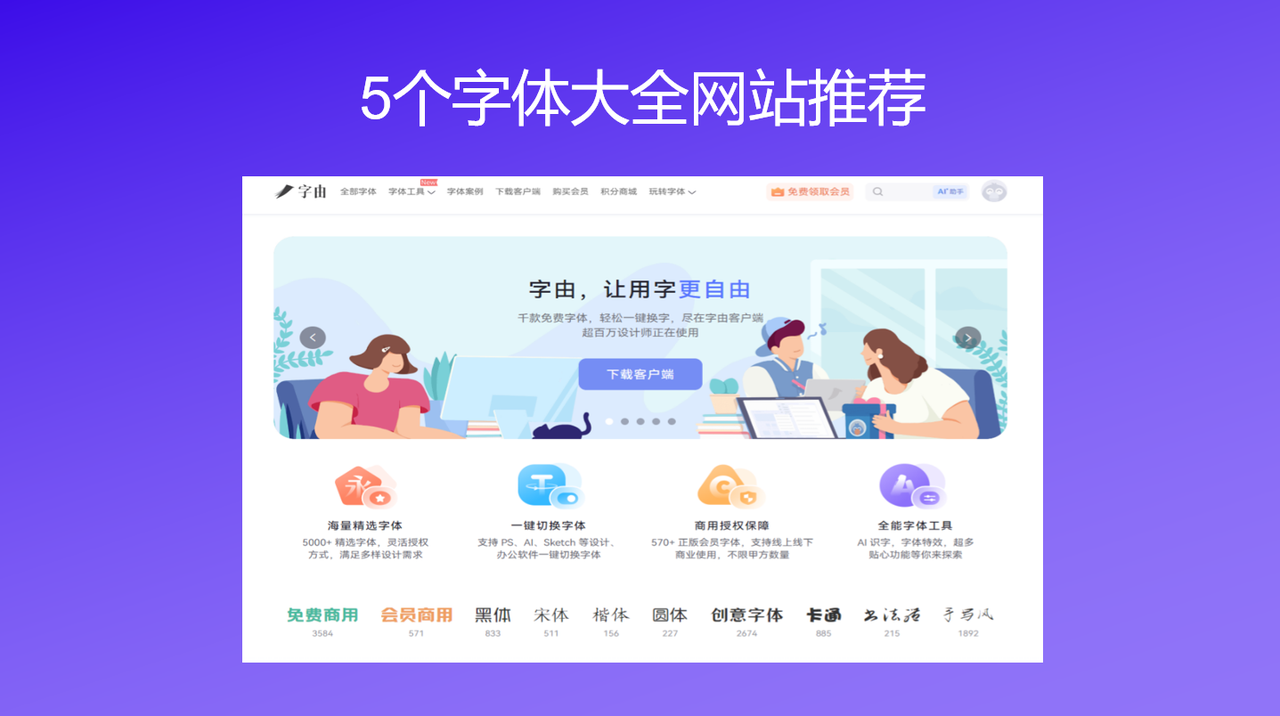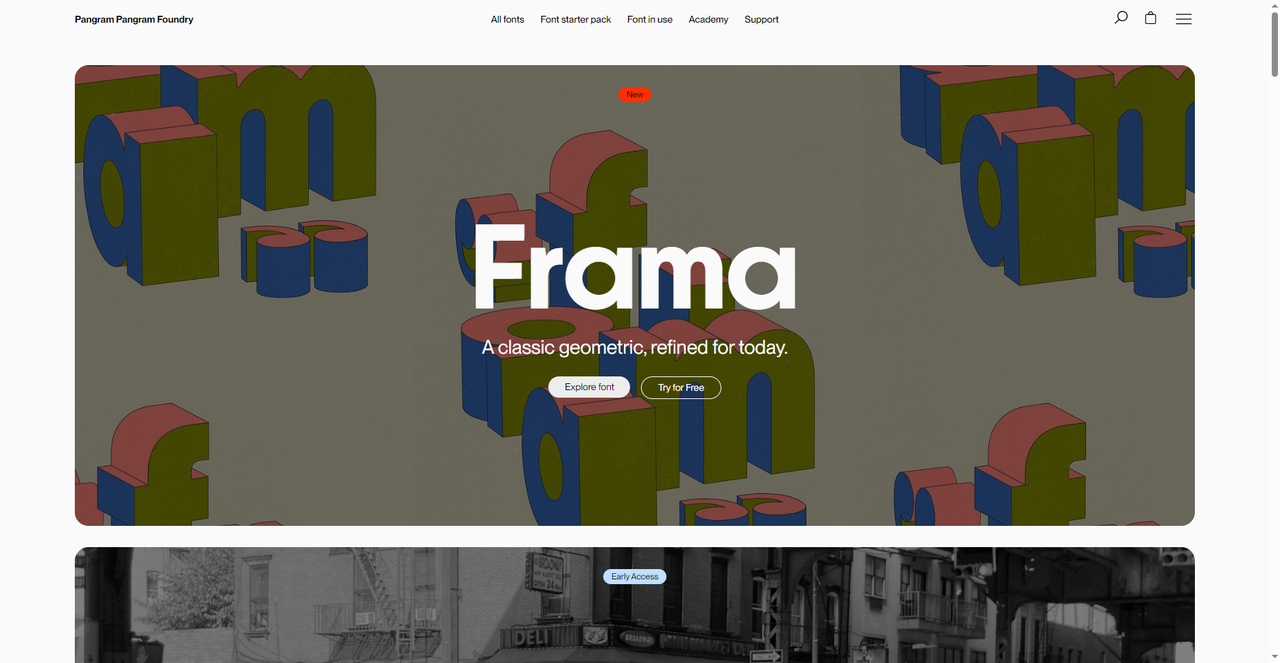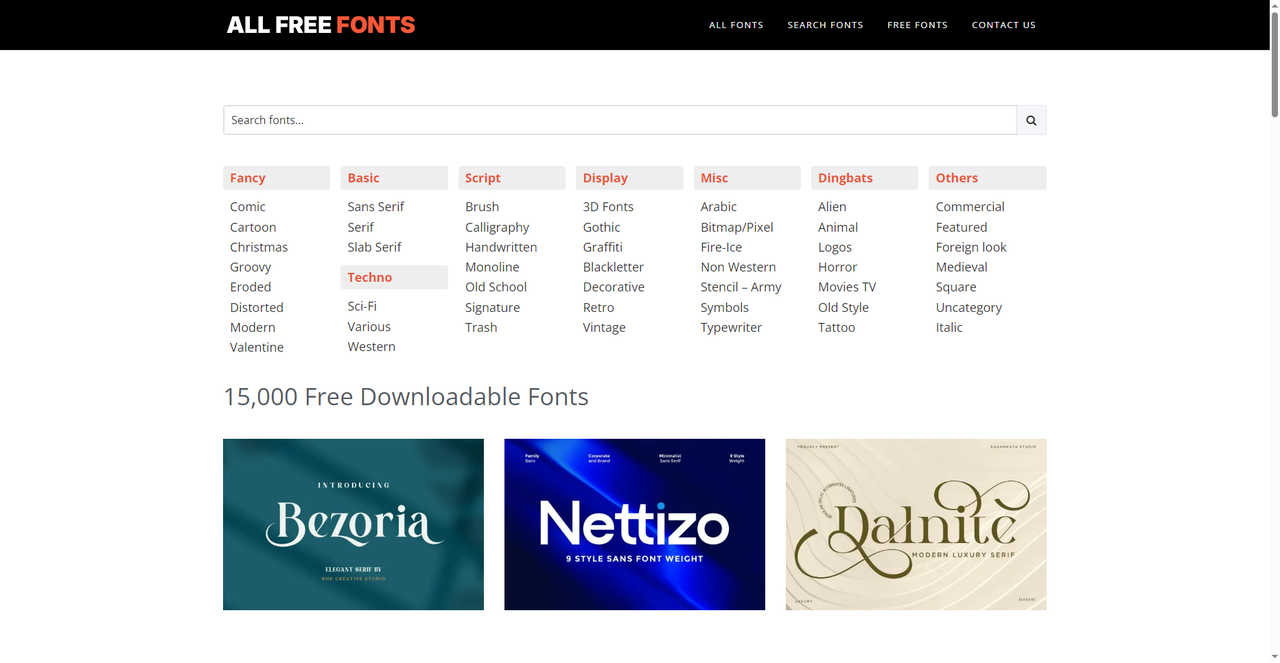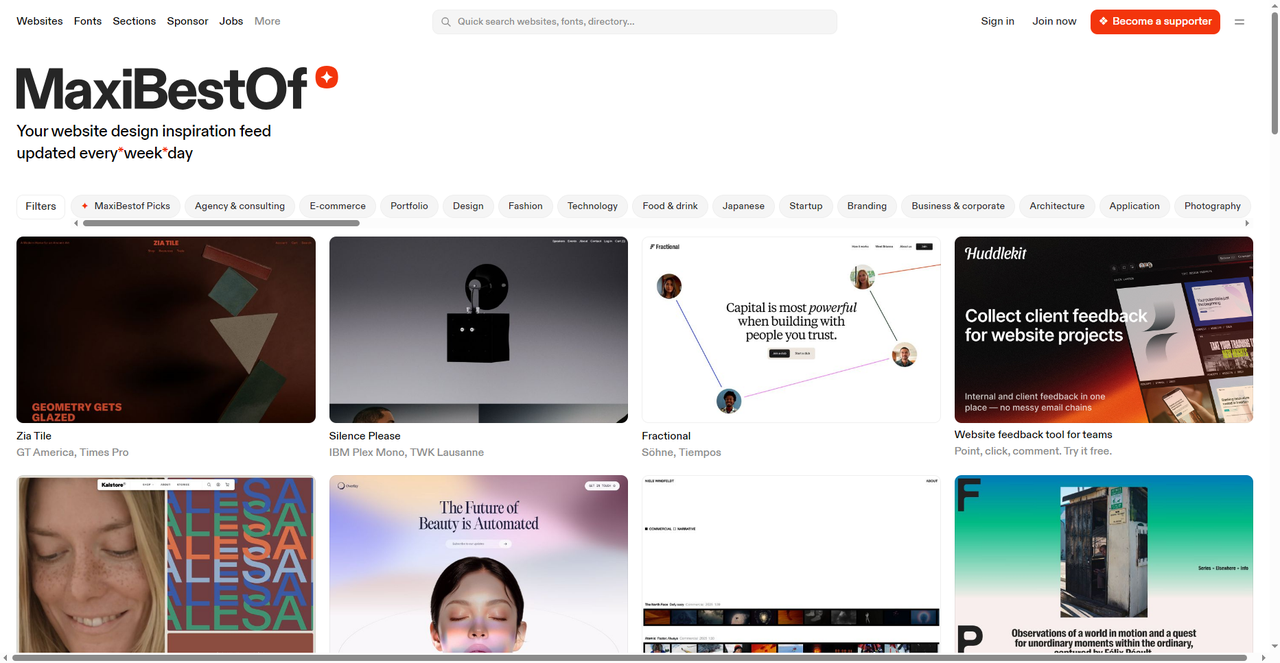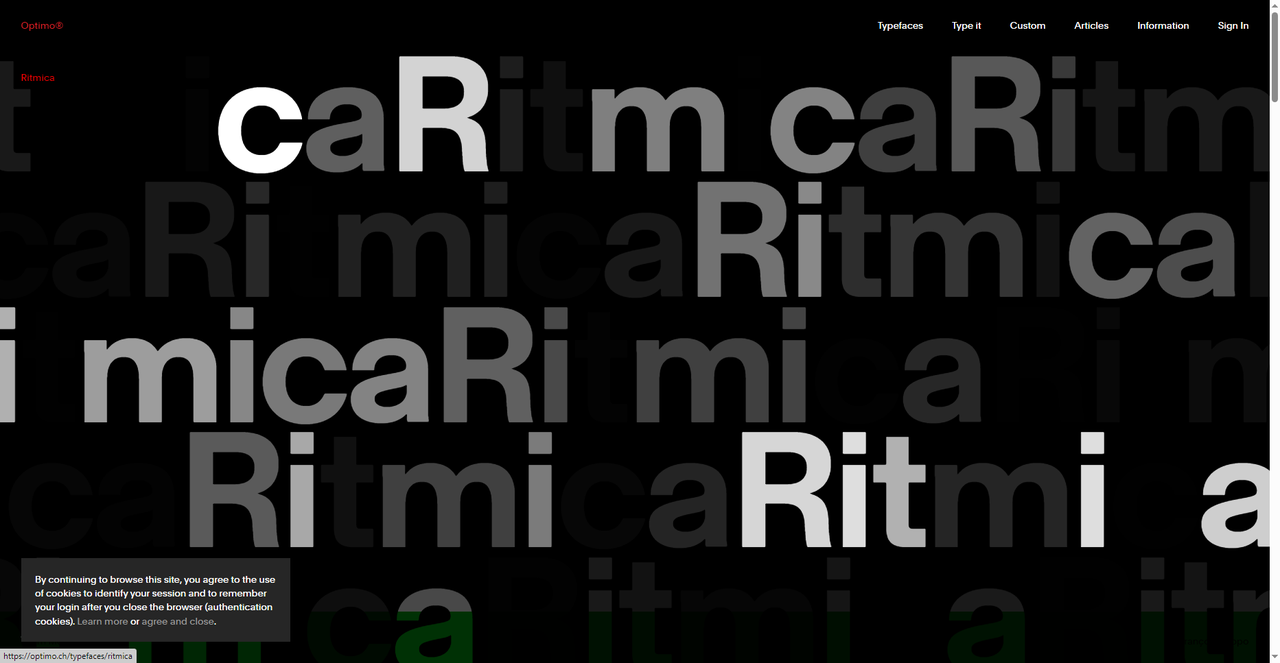
5个字体大全网站推荐,需要的话直接收藏!
电脑里存的字体越来越多?每次做设计光翻字体就要翻半天,在一屏又一屏的缩略图里划来划去,眼睛都花了还是找不到想要的那一款?这些事情都可以通过字体大全网站来一站式解决你的烦恼。有时候不是字体不够多,而是我们缺少一个像字体大全一样的网站,能够帮你把各种风格、各种用途的字体都收齐的地方,所谓的字体大全,不只是字体数量多,更是分类清晰、授权明确,能让你快速锁定目标。今天我就整理了 5 个自用的字体大全网站,需要的记得收藏。
第一个我要推荐的就是字由。它和普通字体下载网站最大的不同,是它直接把 5000 多款字体打包成了一个“字体大全”——你不需要一个一个下载、安装,打开客户端就能用。这 5000 多款精选字体,其中超过 3500 款是免费可商用的,涵盖黑体、宋体、书法体、手写体、艺术体等各种风格。而且字由能够支持在 Photoshop、AI、Figma 等设计软件里一键切换字体,选中文字点一下就能够及时更换。当你纠结于选哪种字体能更加适合画面的时候,这一功能无非能提高你的工作效率。而且 字由还提供个人云字库功能,可以上传本地字体到云端,哪怕是电脑坏了也不用担心里面的字体消失不见,只要你的账号还在,那么字体就都在。
2、 Pangram Pangram
Pangram 是一家总部位于加拿大的独立字体代工厂,它的定位很清晰:做现代、几何风格的高品质字体,同时保持价格也不算很贵。 Frama 的主推审美取向在于“a classic geometric, refined for today”(经典几何,为当下而 refinement)。字体线条干净、结构严谨,带着明显的包豪斯和瑞士设计的影响,但又不会过于冷淡,适合品牌设计、网页标题、海报等需要“现代感”的场景。并且网站内都会提供字体免费试用,通常是有限字数或者是精简字符。除此之外,网站设有 Academy 板块,里面有字体使用教程、设计案例分享,甚至还有一些免费资源。相当于在卖字体的同时,也在做字体教育。
3、All Free Fonts
All Free Fonts 是一个名副其实的“字体大全”,最令人兴奋的是它收录了超过 15000 款 免费可下载字体。这个体量意味着无论你想要什么风格,基本都能在这里翻到。网站左侧的分类栏非常夸张,我数了一下大概有七八十个标签。有按风格分类的,有基础分类,也有按特殊效果和用途场景分类的,甚至还有按字符分类的选项,这种分类方式的好处是,你可以很快速地找到特定场景需要的字体——比如要做万圣节海报,直接点“Horror”;要做纹身设计,点“Tattoo”。不用在一堆字体里盲目翻。在这个字体大全网站里每款字体都标注了授权类型,大部分是免费可商用的,但也有部分仅限个人使用。这方面需要额外注意,不要使用了不能商用的字体!
4、Maxi Best Of
Maxi Best Of 本身不是一个字体下载网站,而是一个网站设计灵感平台——每天更新精选的优质网站案例。但它有一个对设计师特别实用的功能:每个案例下方都会标注该网站使用的字体。你可以看到那些设计奖级别的网站实际用了什么字体,然后去搜索下载或购买。这相当于一个“字体应用实景库”——字体不再是孤立的预览图,而是呈现在真实的设计场景里,你能直观感受到它在排版、配色、布局中的效果。其实也算是另一种意义上的字体大全了!如果不觉得麻烦的话可以先来这里看看有没有喜欢的,再去寻找字体所在的下载链接。需要提醒的是, 这里标注的字体不全是免费的,有些是付费商业字体。但知道了名字,你可以去搜免费替代品,再看是否值得购买。就算不购买,也可以把它当做一个审美学习网站,不论如何都是十分合适的字体网站!
5、Optimo
这一期我也还是选择推荐一款高端字体设计公司,由两位设计师 Francois Rappo 和 Julien Janiszewski 主理。它的名字在专业字体圈里就是“品质”的代名词。从主页我们就可以看出 Optimo 的调性——线条干净利落,比例精准考究,带着瑞士设计特有的严谨和克制,但又不会显得冷漠。每一款字体都像是一件精心打磨的作品,适合对字体质感要求极高的项目。Optimo 的字体库不算大,但每一款都很能打。比如 Univers Next、F Grotesk、Plain 等,都是很经典的字体,可以理解为经典字体大全网站。如果你正在做高端品牌项目、杂志画册,或者单纯想看看顶级字体设计长什么样,Optimo 值得收藏!